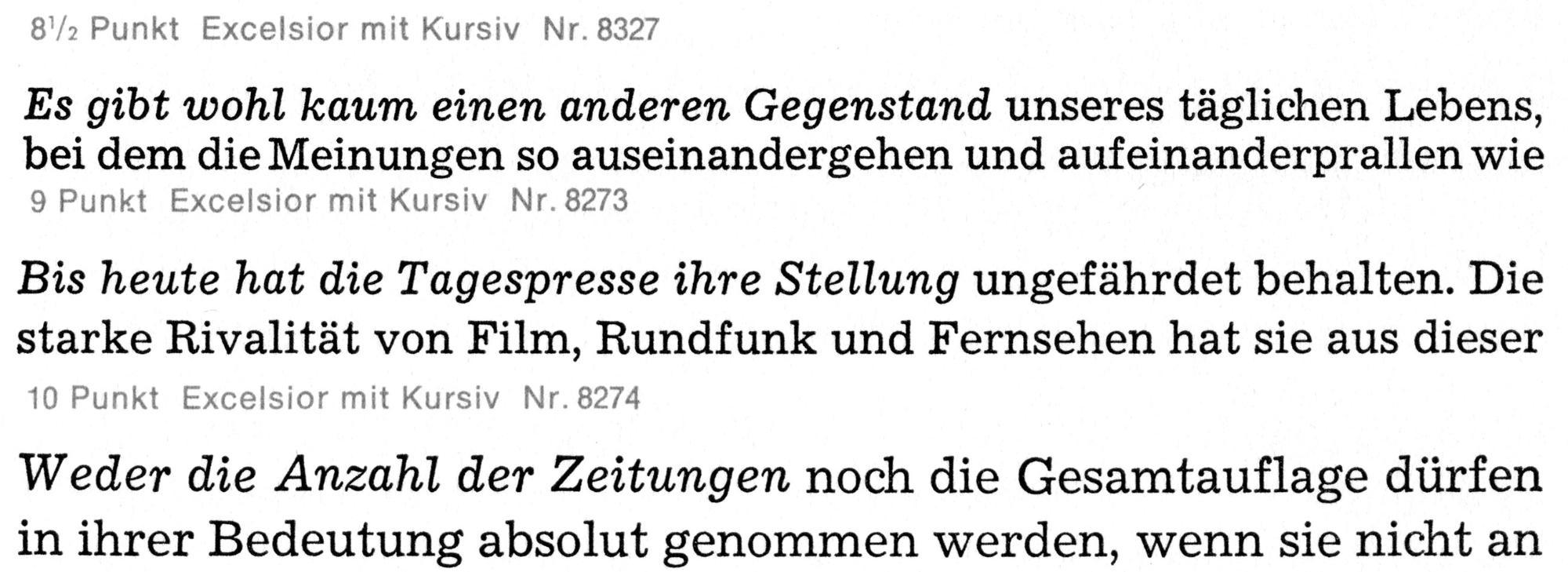
Suche Font, den "Der Spiegel" in den Fünfzigerjahren für den Fließtext verwendet hat
Wer kann weiterhelfen: Welchen Font hat der Spiegel für den Fließtext in den Fünfzigerjahren verwendet?
Ich glaube, es handelt sich um eine Excelsior oder die News 702.
An die Excelsior hab ich auch gleich gedacht.
Moin, falls Ihr vergleichen wollt, hier ein Excelsior Bleisatzscan aus: „Linotype-Schriften“ – Matrizen für Bleisatzmaschinen; 1976